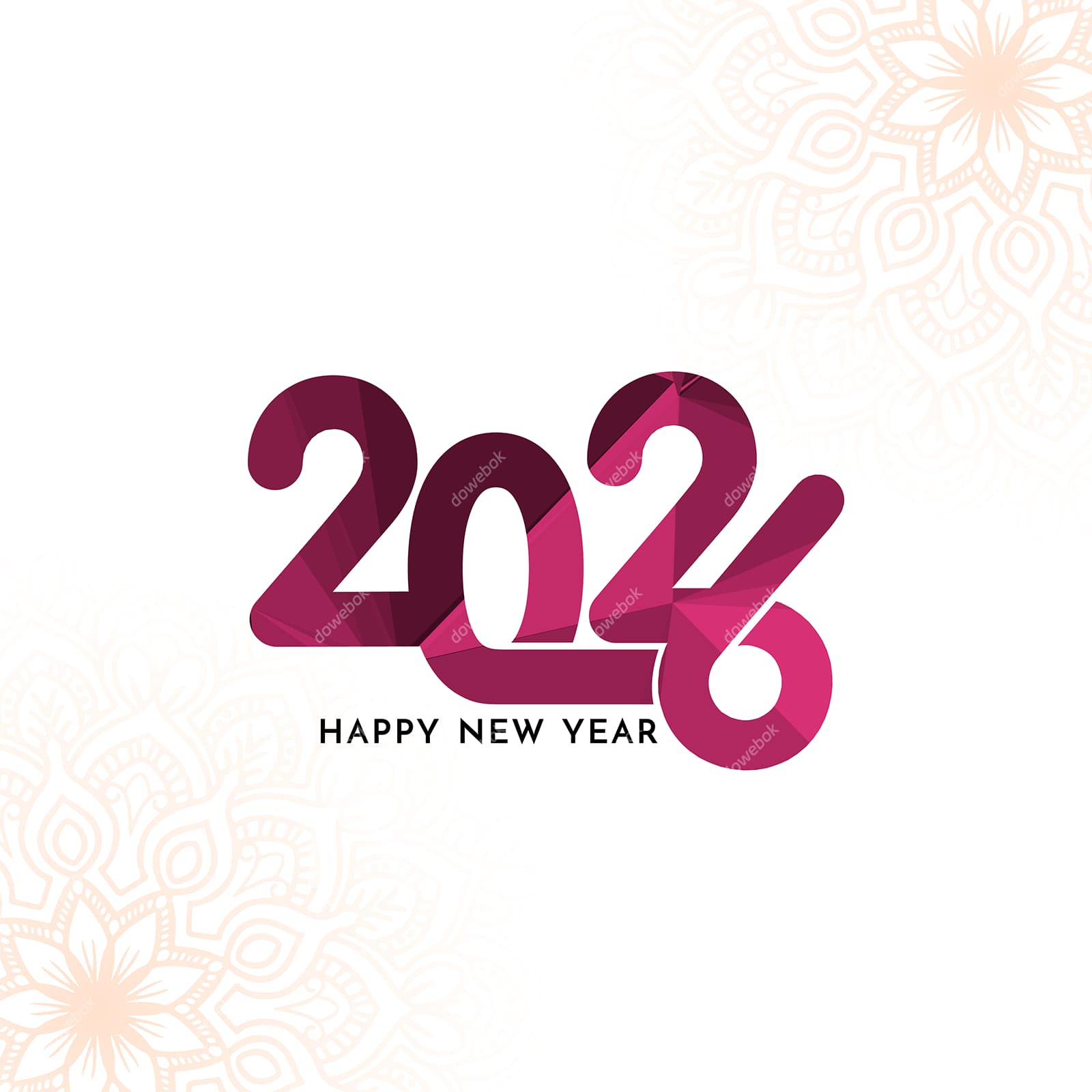
这是一款紫红色渐变数字设计的 2026 新年快乐矢量素材,白底衬着浅米色曼陀罗花纹,雅致柔和。画面中央是紫红渐变的几何拼接 “2026” 字体,立体质感中透着精致,下方配黑色 “Happy New Year” 英文。整体以低饱和装饰与渐变字体结合,既借紫红传递新年的温婉喜庆,又以几何设计显现代感,适配贺卡、电子祝福等场景。